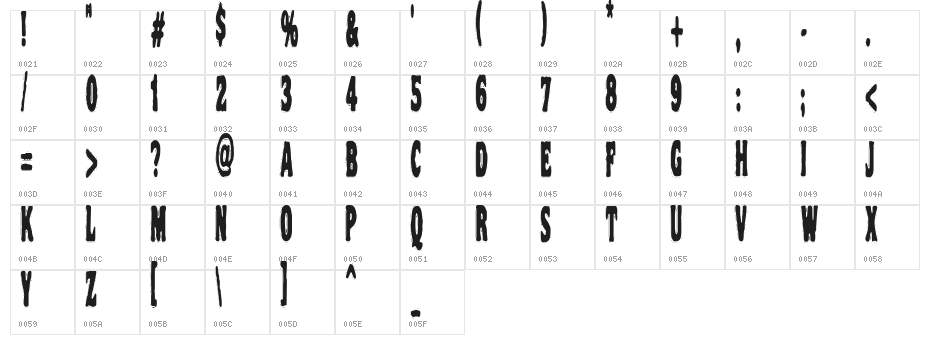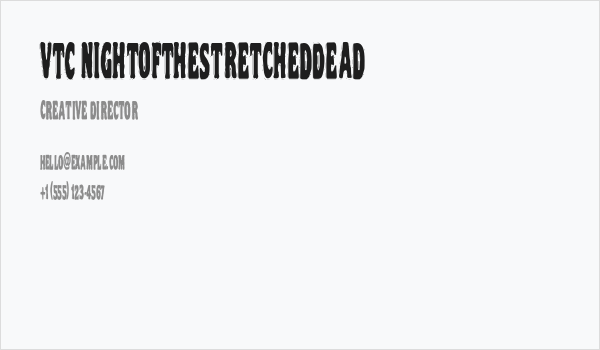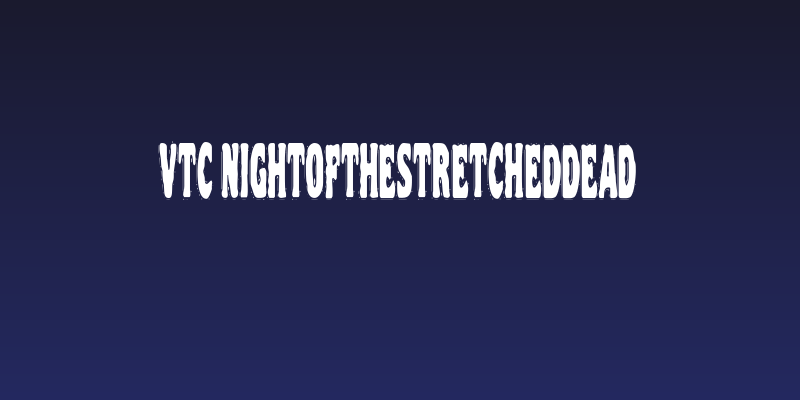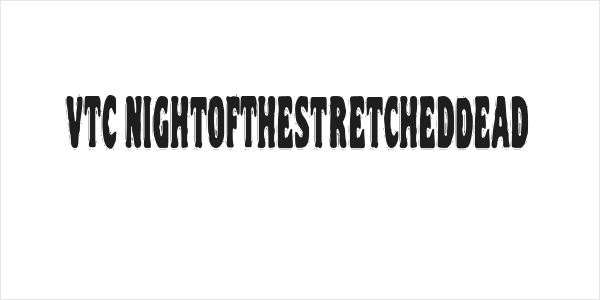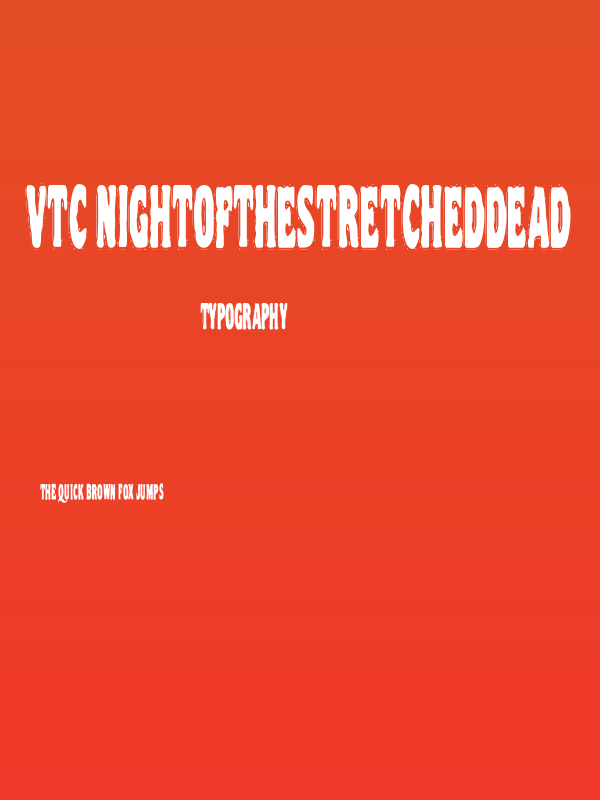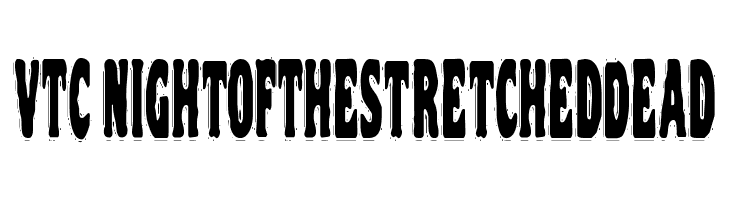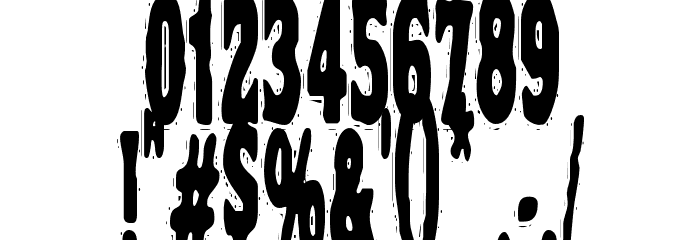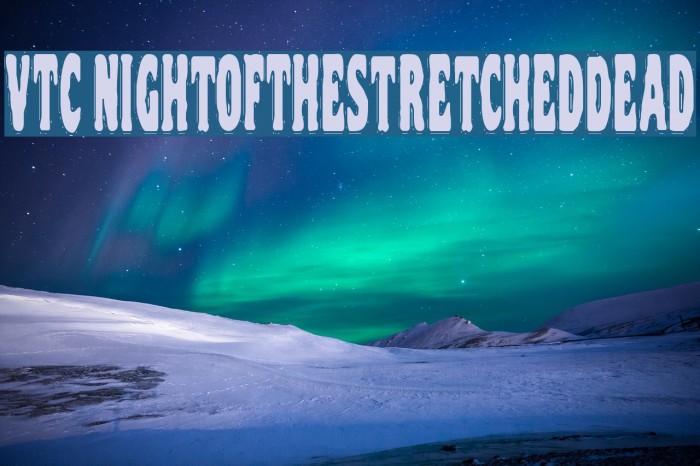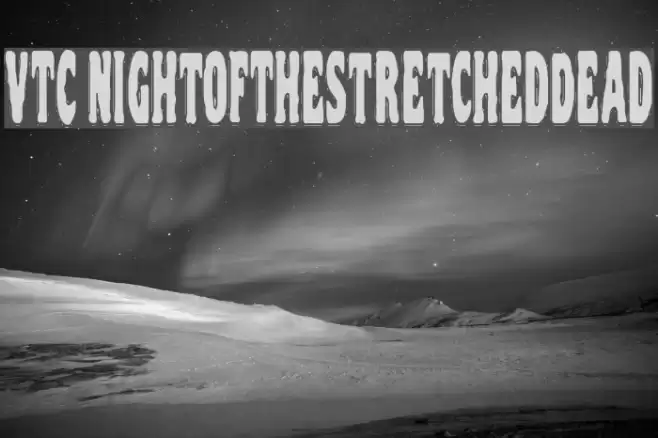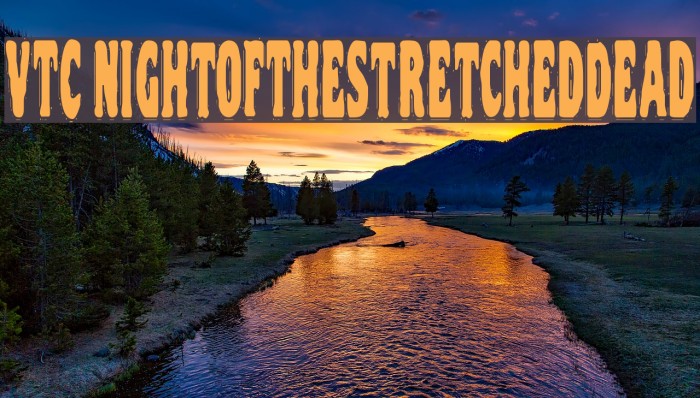
VTC NightOfTheStretchedDead Font
| Proyectos propuestos | Ideal for Halloween-themed posters, horror movie titles, haunted house flyers, and spooky event invitations. |